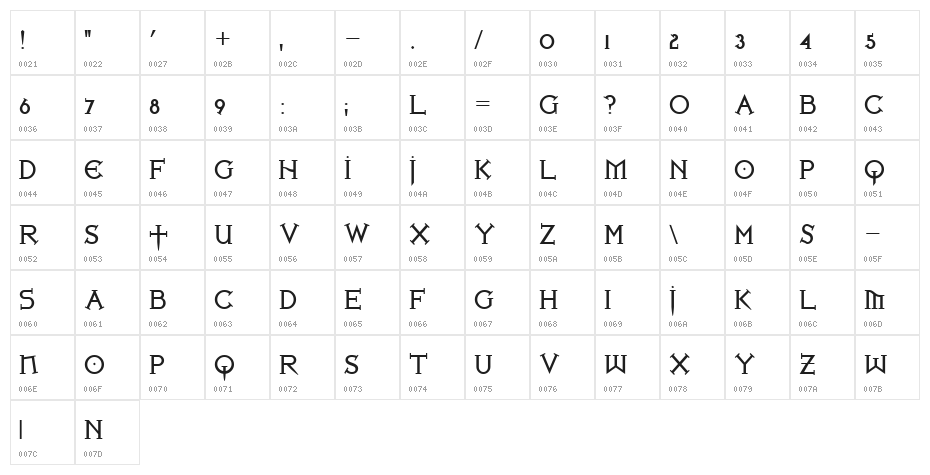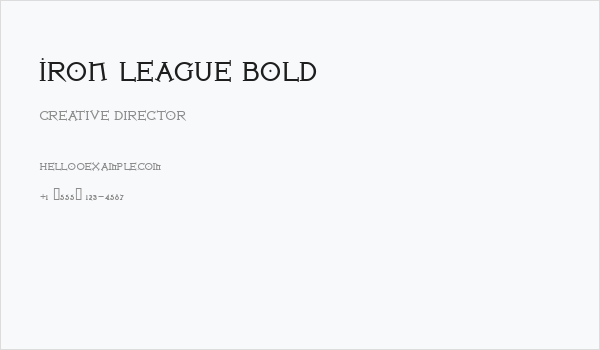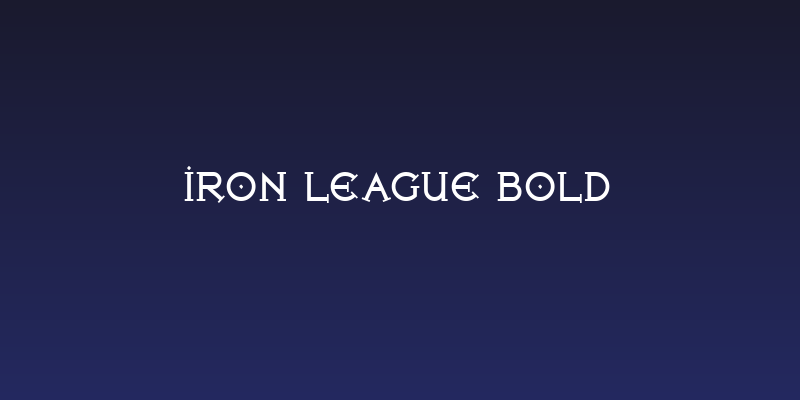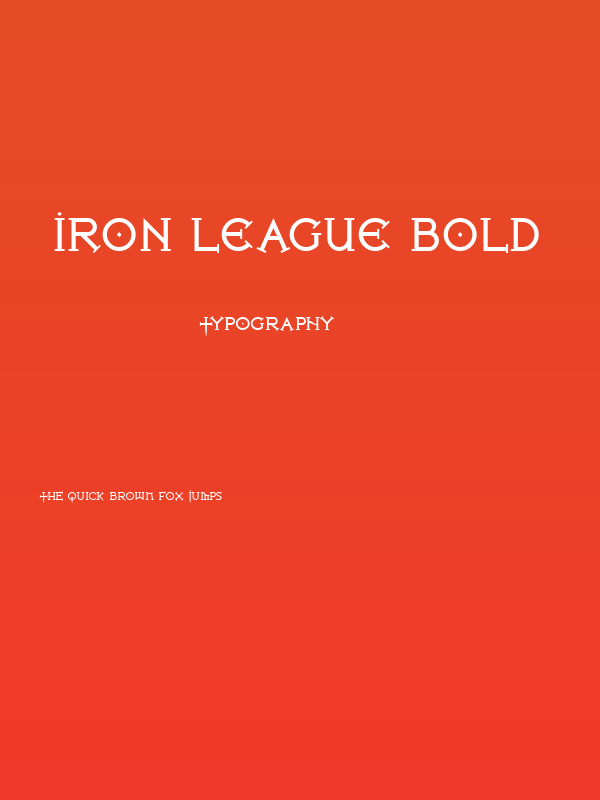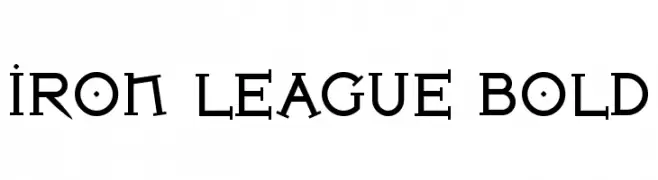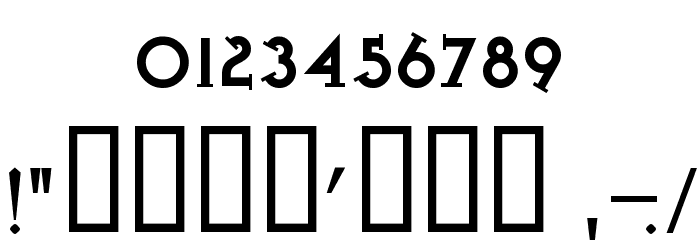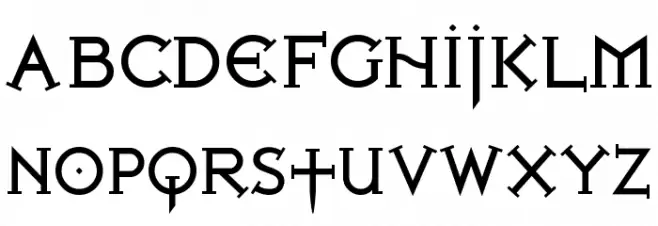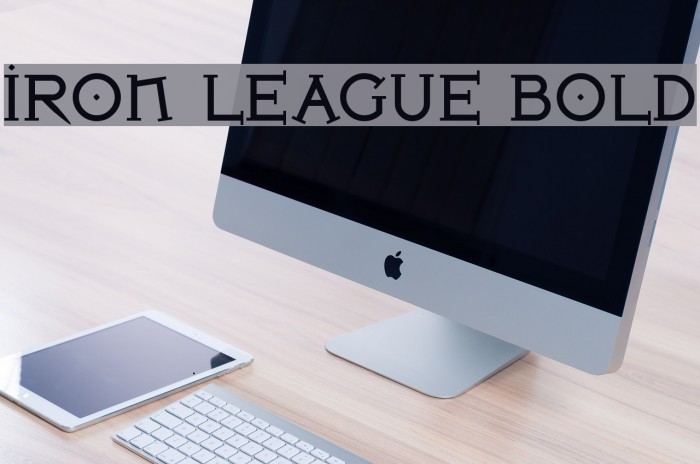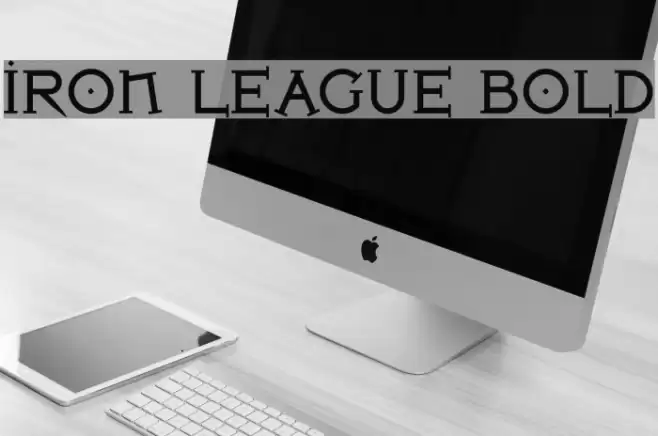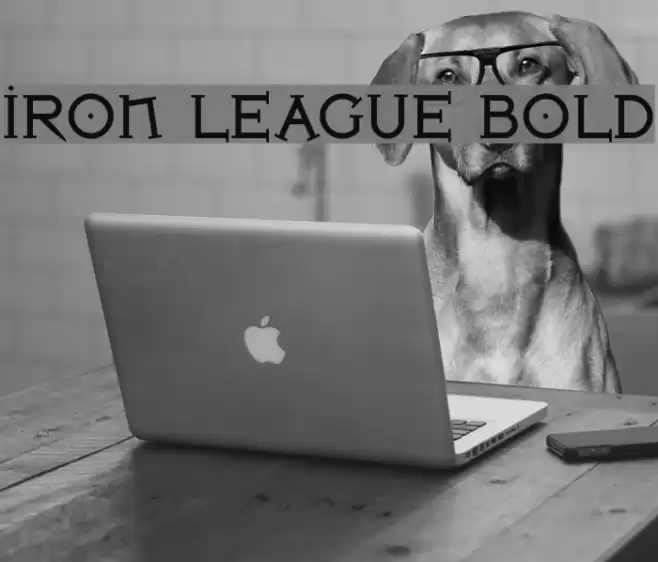
Iron League Bold Font
✎ Gothic
| Categorii | Gothic |
| Stil general | Modern, Industrial |
| Proiecte propuse | Ideal for branding, logos, posters, and any design requiring a bold, authoritative look. |